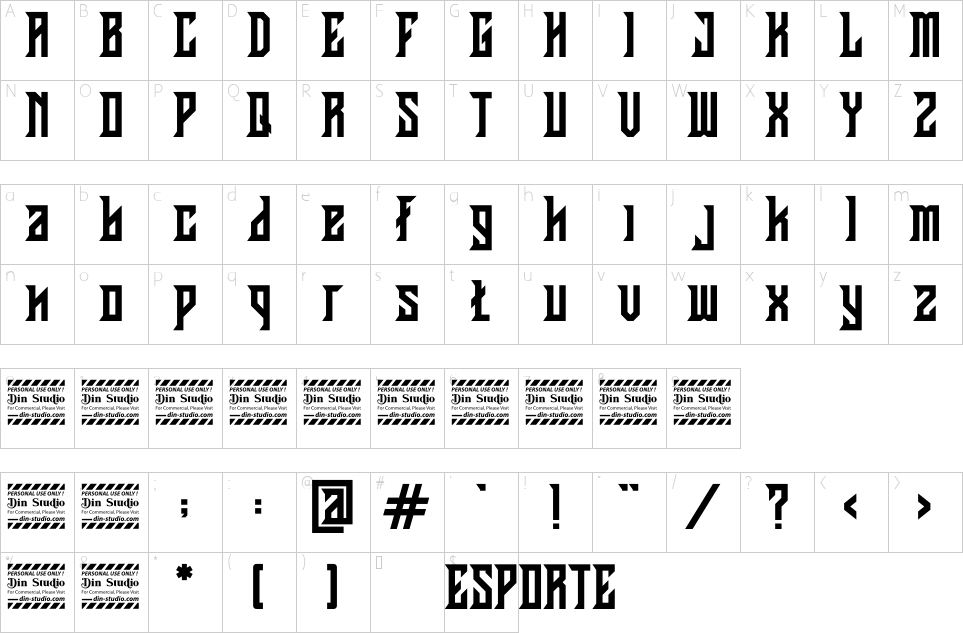
A Esporte Font é uma elegante escolha para qualquer projeto que valorize a simplicidade e a legibilidade. Desenvolvida pela Din Studio, essa fonte traz um toque moderno ao seu design gráfico ou layout web. Com 9.737 downloads até agora, a Esporte se destaca pelo seu equilíbrio entre elegância e facilidade de leitura. Ideal para aplicativos de jogos, sites esportivos ou qualquer projeto que valorize o bom desempenho visual em diferentes formatos de tela e tamanhos de fonte. A Esporte Font é uma excelente opção para quem procura uma fonte moderna e elegante sem abrir mão da legibilidade necessária em contextos digitais dinâmicos.